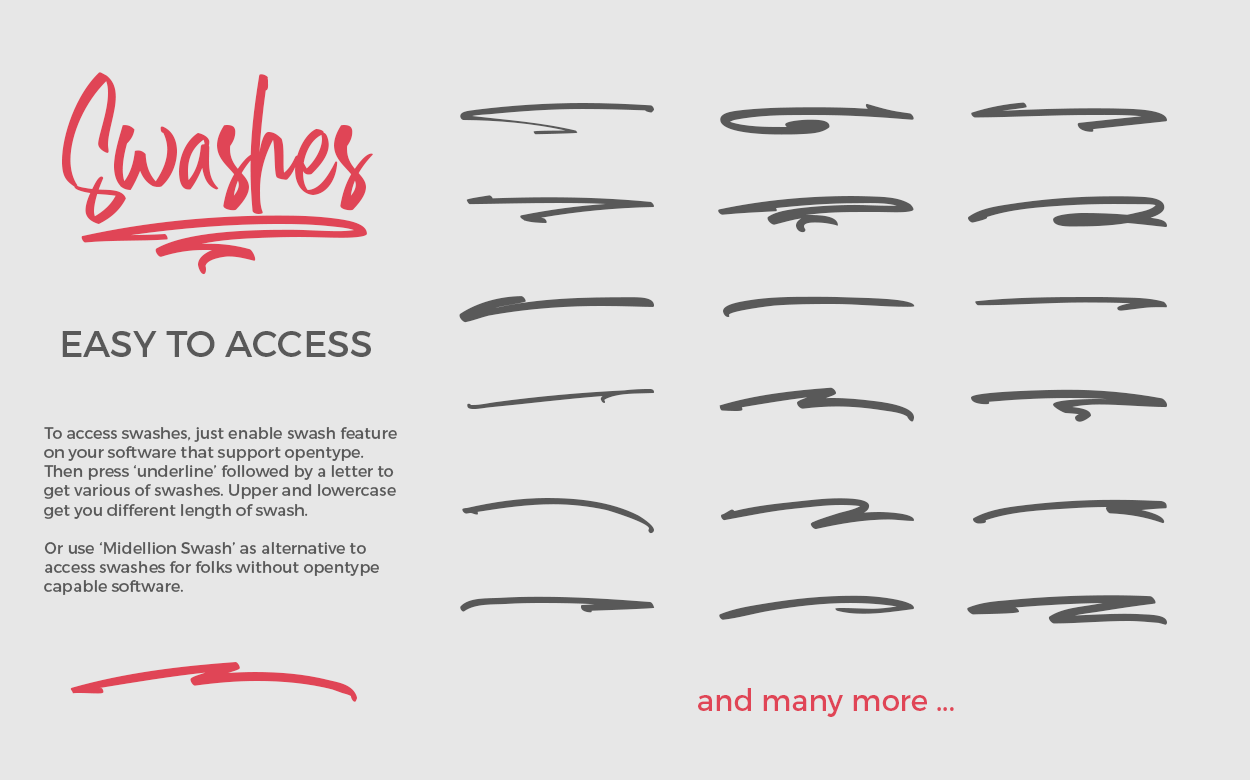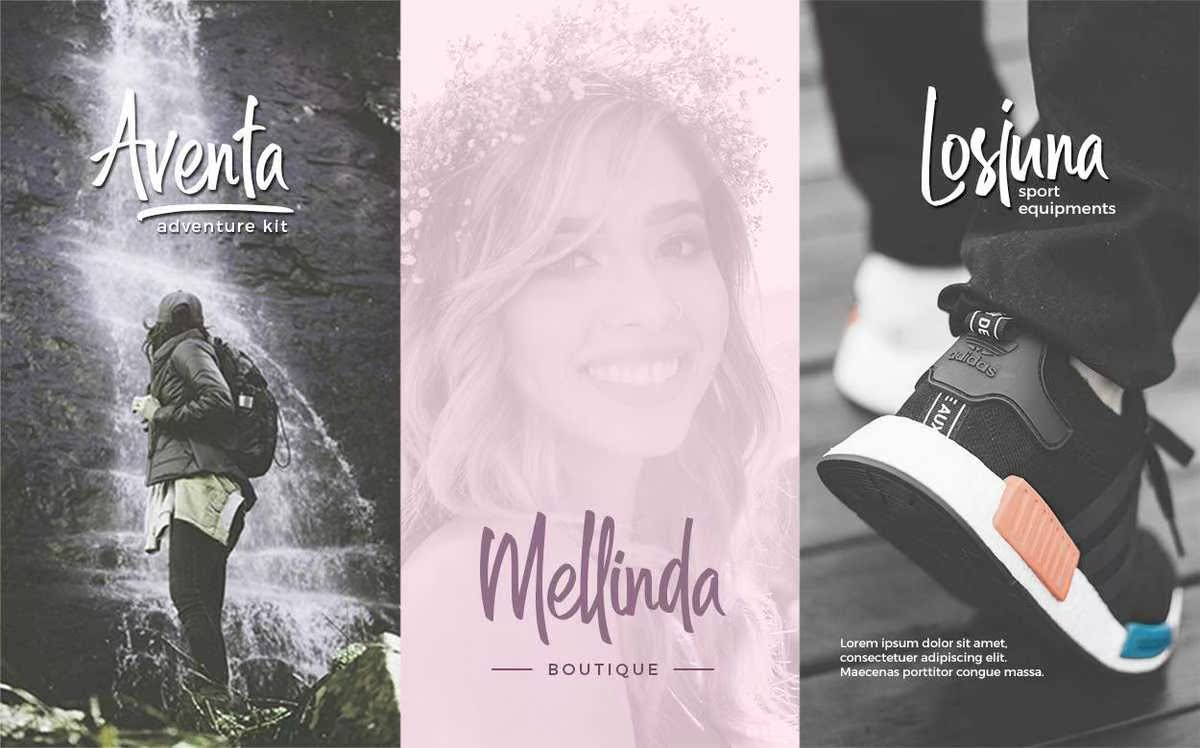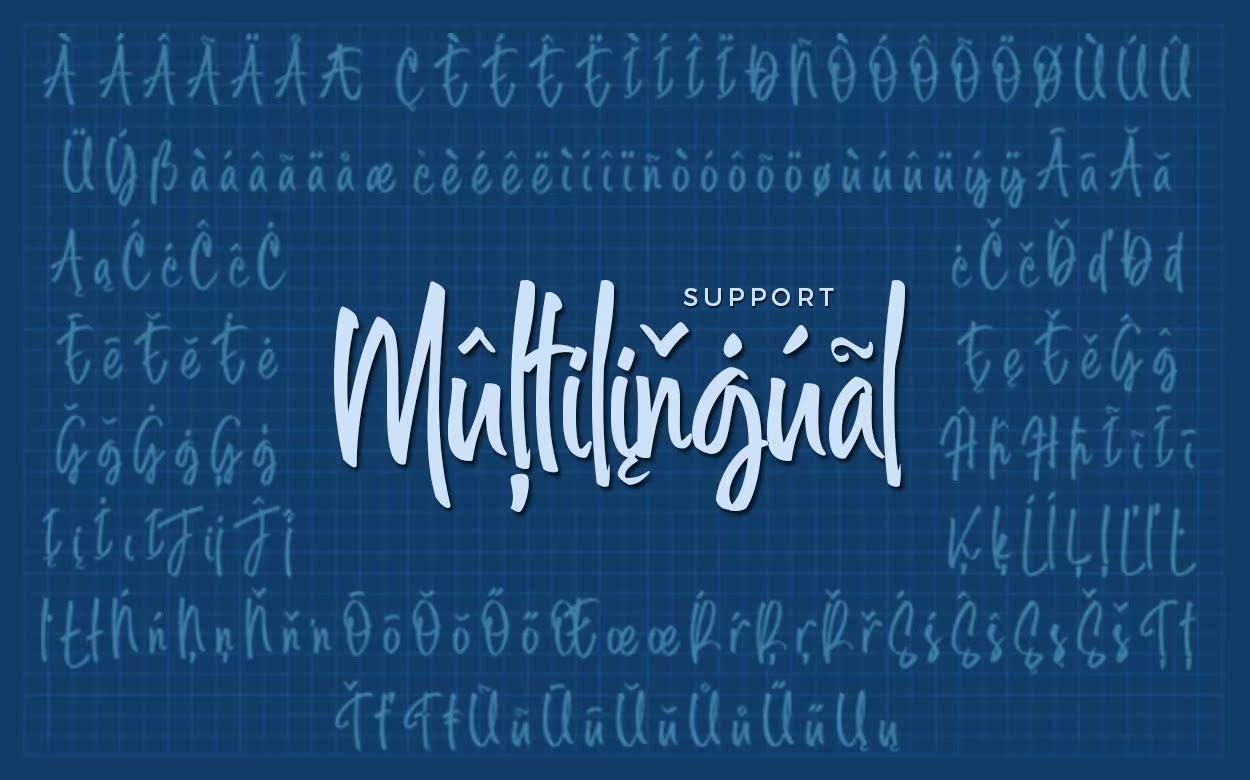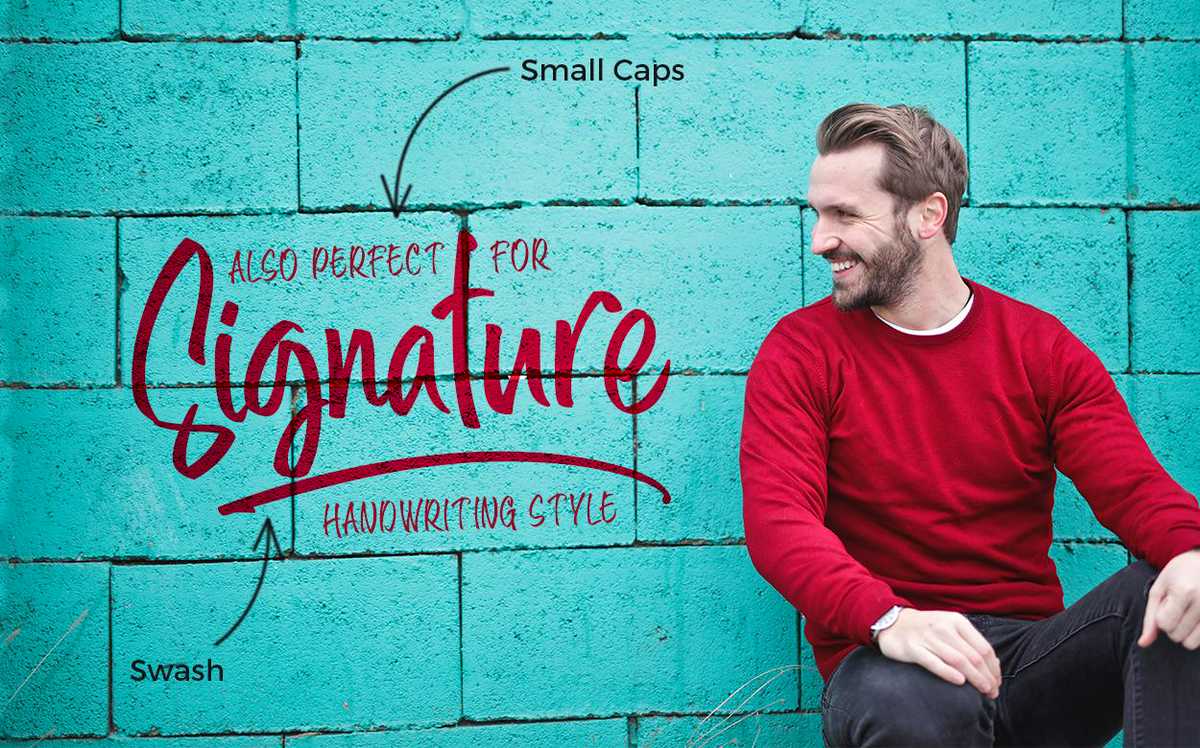
Hidude,让我们为您介绍一下:Midelion。一个具有现代样式和内置字体功能的箭头手写体脚本。此字体具有支持多种语言和多种清洗功能,包括在竞争对手地区,使您可以轻松访问这些字体,即使您的软件不支持OpenType.Hidude,让我们介绍一下您:Midellion。一种具有现代NSTYLE和内置ENTYPE功能的箭头手写体脚本。该字体具有支持多种语言和多种清洗功能,包括在竞争对手地区,使您可以轻松访问这些字体,即使您的软件不支持OpenType。